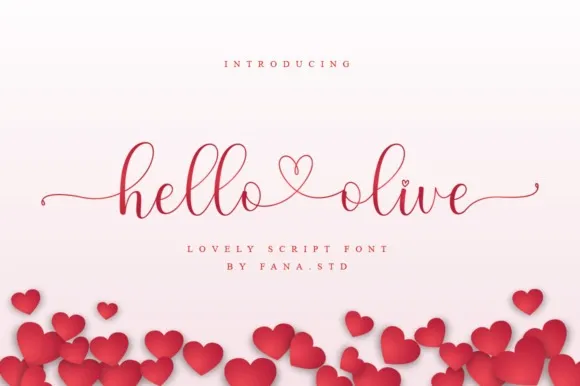
Hello Olive Font – Download Grátis
Esta fonte é uma delicada tipografia feminina que transmite beleza, elegância e apelo visual. Desenvolvida pelo designer fanastudio no formato de letra script, ela se destaca pela autenticidade das suas linhas curvas e formas fluidas. Perfeita para criação de convites de casamento incrivelmente bonitos, arte de cartões postais maravilhosos, posts em redes sociais que chamam a atenção e tarjetas de cumprimento encantadoras. Seja você quem adquirir esta fonte, certamente se apaixonará pela sua personalidade única e elegante. Sua versatilidade permite usá-la em muitos projetos gráficos, tornando-a uma escolha perfeita para qualquer designer que busca um ar de delicadeza e sofisticação no seu trabalho.